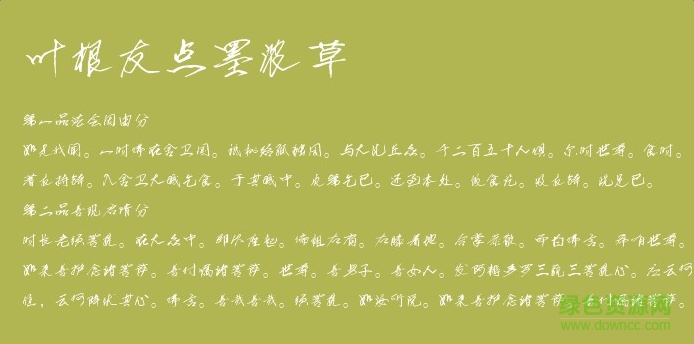
葉根友點(diǎn)墨濃草字體是一款葉根友類草書風(fēng)格字體軟件,點(diǎn)墨濃草體盡顯草書魅力,字體筆畫行如流水,十分優(yōu)美,整體效果生龍活虎、放浪不羈,還有更多好看字體歡迎來綠色資源網(wǎng)下載體驗(yàn)!
葉根友點(diǎn)墨濃草是一款草書的字體,喜歡草書字體的朋友有福了,這款相信能入您的法眼,字與字之間一氣呵成,點(diǎn)墨之間,濃濃的草書味道,故取名點(diǎn)墨濃草。
該字體盡顯草書的霸氣特點(diǎn),字體筆畫相互連接,看似雜亂卻不失基本工整,非常的文雅好看,是草書里面比較大方得體的了。